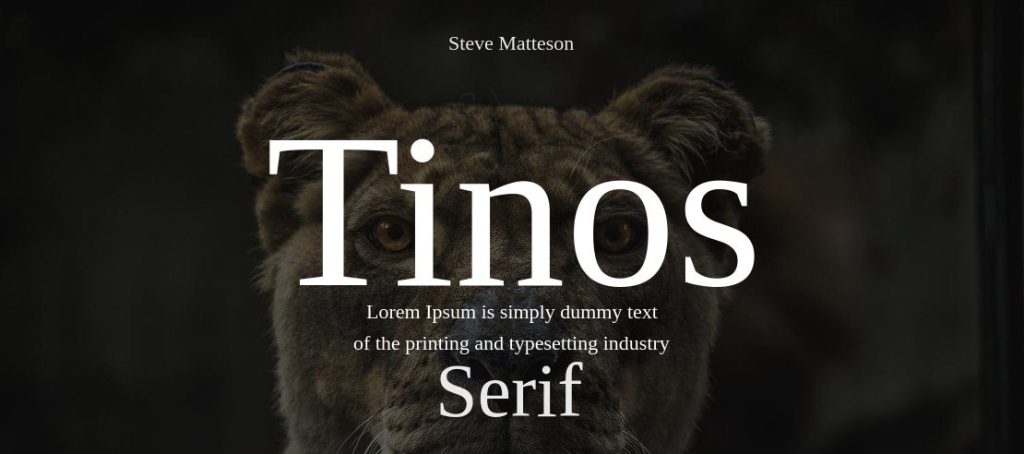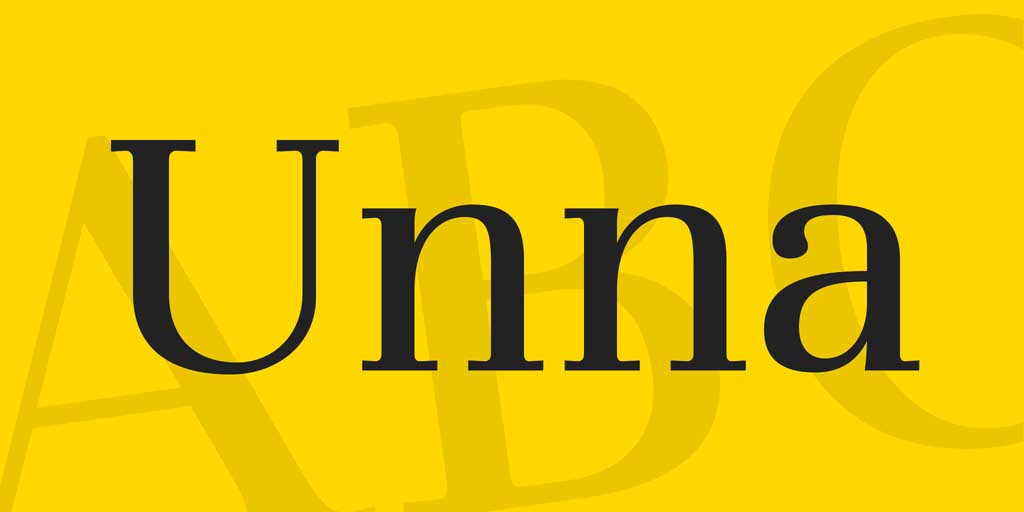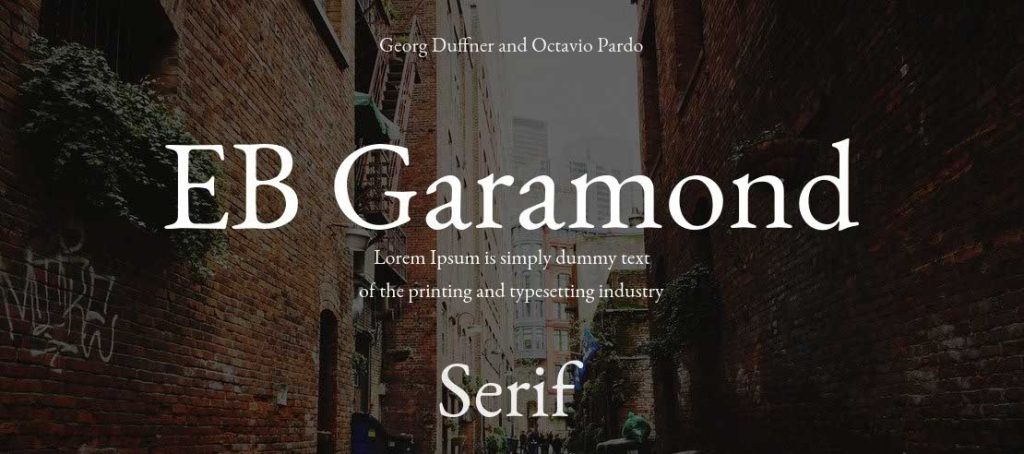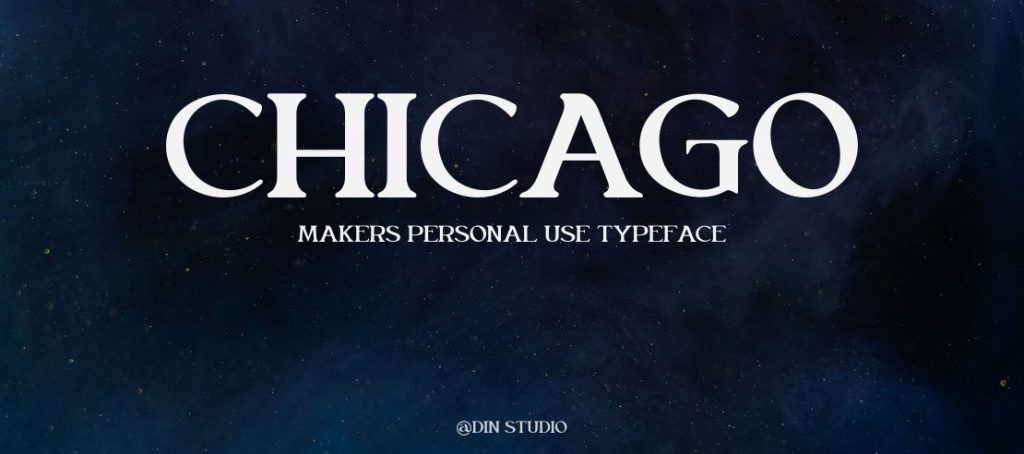
19+ Font Chữ Có Chân Đẹp, Cổ Điển, Việt Hóa Cho Designer
Vẻ đẹp cổ điển và thanh lịch của font chữ có chân giúp thiết kế của bạn trở nên tinh tế hơn. Lựa chọn font chữ đôi khi là một nhiệm vụ khó khăn và đòi hỏi nhiều thời gian của nhà thiết kế. Terus sẽ giới thiệu cho bạn các font có chân đẹp mắt trong bài viết sau để bạn tham khảo cho dự án thiết kế của mình.
I. Font chữ có chân là gì?
Serif font, còn được gọi là font chữ có chân, là loại font chữ có các nét móc hoặc chân nhỏ ở đầu hoặc cuối mỗi ký tự.
Nhiều thiết kế sử dụng font chữ có chân thường, đặc biệt là trong các văn bản hành chính, báo chí hoặc sách xuất bản. Một số thương hiệu sang trọng như Dior, Gucci và Tiffany & Co,… sử dụng font serif trong thiết kế logo của họ vì họ tin rằng những font chữ có chân mang lại cảm giác chuyên nghiệp và sang trọng.
II. Tổng hợp 19+ font chữ có chân đẹp mắt
Terus sẽ giới thiệu những font chữ có chân đẹp mắt từ những font serif cổ điển cho đến những biến thể hiện đại hơn, giúp bạn tìm được những font chữ phù hợp nhất cho thiết kế của mình.
1. Playfair Display
Playfair Display có khả năng tạo ấn tượng thanh lịch và độc đáo cho người nhìn. Playfair Display, được phát triển bởi Claus Eggers Sørensen, lấy cảm hứng từ các kiểu chữ serif cổ điển của thế kỷ 18, nhưng được sửa đổi để phù hợp với thị hiếu hiện đại.
Playfair Display cung cấp sự cân bằng tuyệt vời giữa nét thanh và nét đậm, đảm bảo rằng nội dung dễ đọc và thoải mái cho mắt. Playfair Display có thể được sử dụng làm tiêu đề, bảng quảng cáo và các thành phần quan trọng của thiết kế. Playfair Display là lựa chọn tuyệt vời cho các thương hiệu và những người muốn tạo ra ấn tượng với vẻ đẹp sang trọng, thanh lịch và dễ đọc.
2. Garamond
Claude Garamond đã tạo ra Garamond, một font chữ serif thanh lịch và cổ điển vào thế kỷ 16. Font chữ này, được tạo ra bởi Claude Garamond vào thế kỷ 16, mang đậm dấu ấn của thời kỳ Phục Hưng và được biết đến với sự tinh tế và thanh lịch.
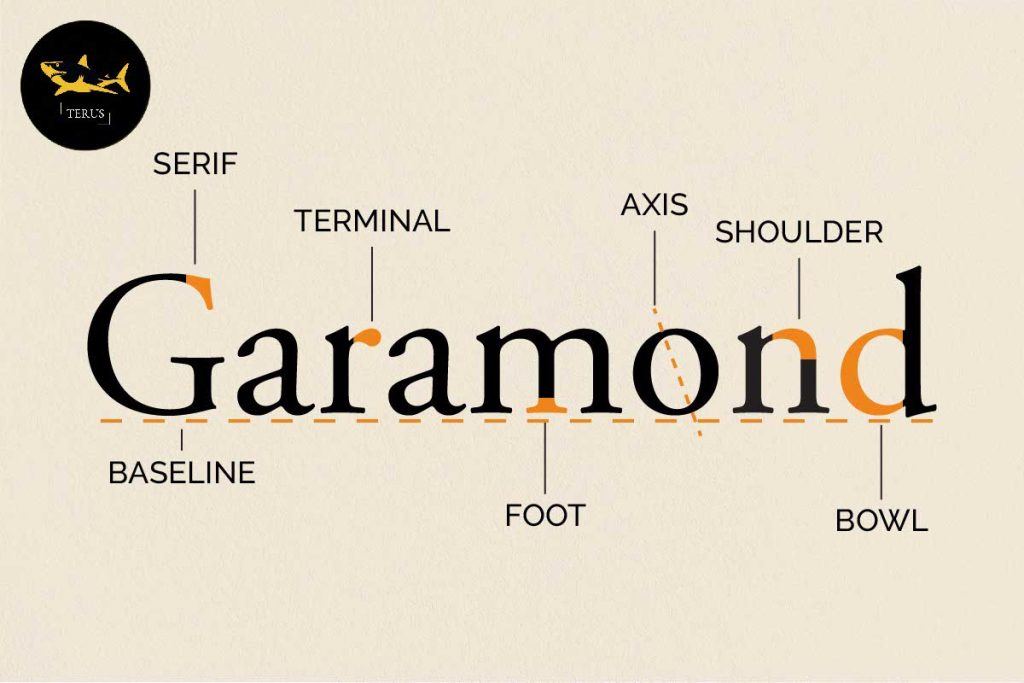
Các đặc điểm chung của Garamond bao gồm các đường nét mềm mại, đối xứng và chân nhỏ, mang lại cho nó vẻ ngoài cổ điển và thanh nhã. Thông thường, font chữ có chân này được sử dụng cho văn bản trong sách, tạp chí và báo, đặc biệt là văn học hoặc các tác phẩm chuyên ngành như văn học, triết học và lịch sử.
3. Didot LT Std Italic
Font Didot LT Std Italic là một biến thể của font chữ Didot, được coi là một trong những font chữ được sử dụng phổ biến nhất hiện nay. Các đường nét cong mềm mại và sự nghiêng nhẹ về phía trước là những đặc điểm nổi bật của Didot LT Std Italic, mang lại cảm giác thanh lịch và uyển chuyển. Các ký tự cân đối và tương phản hoàn hảo, tạo nên một kiểu chữ dễ đọc và phù hợp với nhiều loại dự án thiết kế.
4. Cardo
Font chữ Cardo là một font chữ có chân việt hóa miễn phí dựa trên tiếng Latin và Hy Lạp cổ điển. Cardo, được tạo ra bởi David Perry, mang lại cho bất kỳ văn bản nào cảm giác cổ điển và độc đáo, đặc biệt là các tác phẩm nghệ thuật, sách, văn học cổ điển và tài liệu học thuật.
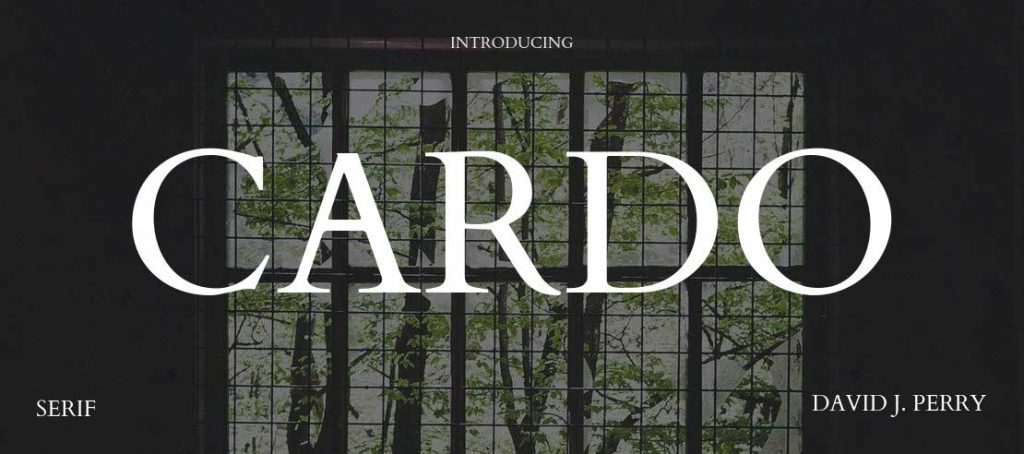
Cardo hỗ trợ nhiều ngôn ngữ, bao gồm tiếng Việt, và có nhiều ký tự độc đáo. Font chữ này có sự cân bằng tuyệt vời giữa nét thanh và nét đậm, giúp người xem đọc văn bản dễ dàng hơn và mang lại cảm giác dễ chịu cho mắt. Một số người cũng sử dụng Cardo cho các loại sách, tạp chí, brochure và catalogue cao cấp.
5. Lora
Cyrus Highsmith đã tạo ra Lora, một font chữ serif hiện đại. Lora là một font chữ serif linh hoạt và hiện đại, phù hợp cho cả in ấn truyền thống và ấn phẩm kỹ thuật số. Lora có khả năng tạo ra cảm giác sang trọng và thanh lịch cho các thiết kế nhờ các nét chữ thanh mảnh và sắc nét. Lora là một lựa chọn tuyệt vời để thiết kế logo hoặc dùng làm tiêu đề vì nó có độ tương phản vừa phải và ký tự dễ đọc.
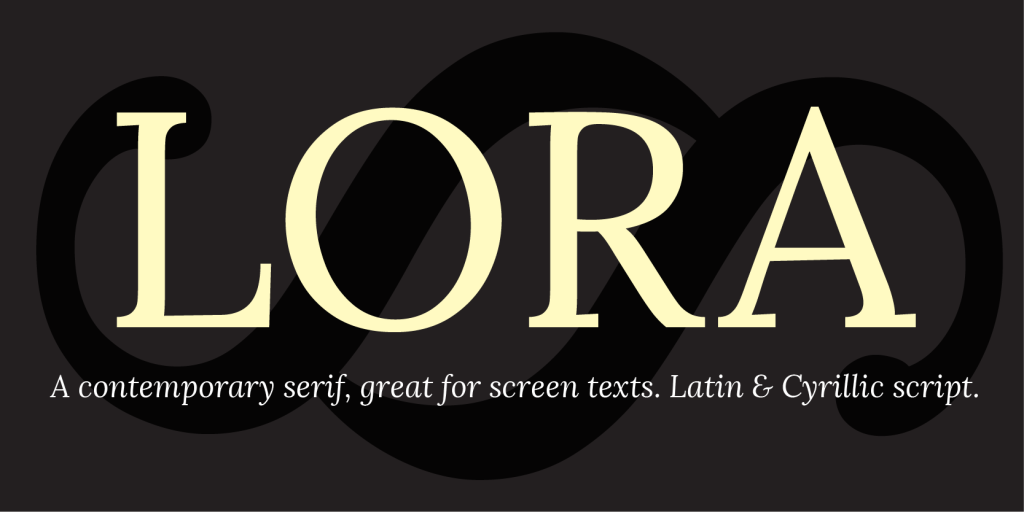
6. Prata
Prata cũng là một font chữ có chân việt hóa hiện đại do Cyrus Highsmith thiết kế. Prata là một biến thể của họ chữ Didone, một loại font serif ra đời vào đầu thế kỷ 19. Ký tự với các móc hình tam giác tạo cảm giác vững chãi và nhẹ nhàng.
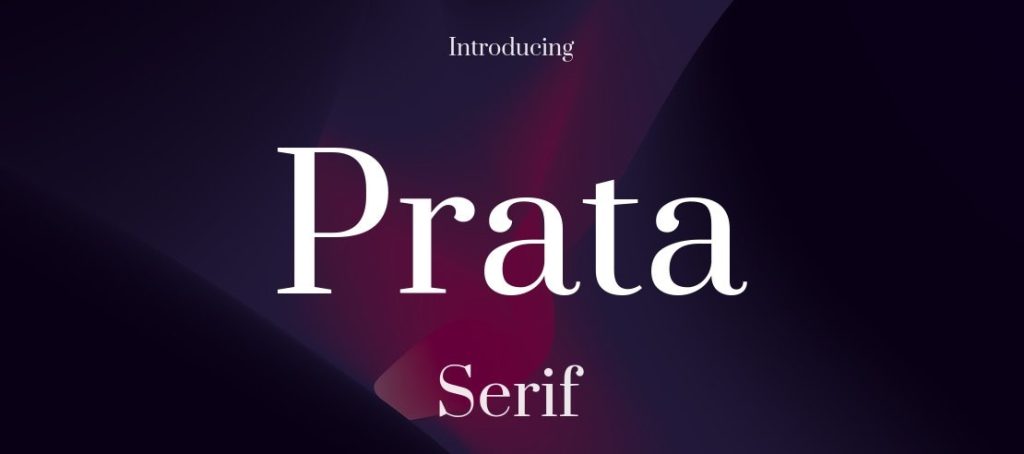
7. Cormorant
Cormorant là một font chữ có chân đa năng và sang trọng có nhiều biến thể, phù hợp với nhiều loại thiết kế như biển hiệu, ấn phẩm và logo thương hiệu. Kiểu dáng thanh lịch và độc đáo của nó mang đến sự tinh tế cho mọi dự án. Ngoài ra, việc kết hợp font chữ này với các font chữ khác và các yếu tố thiết kế khác là đơn giản.
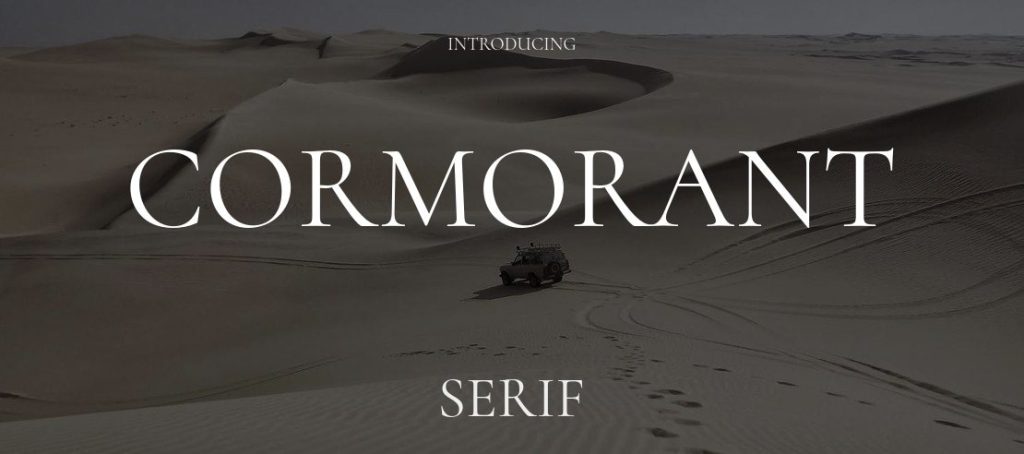
8. Vidaloka
Năm 2011, các nhà thiết kế đồ họa Alexei Vanyashin và Olga Karpushina đã thiết kế Vidaloka. Nhờ đặc điểm dễ đọc ở kích thước lớn, đây là một font tuyệt vời cho các tiêu đề và đoạn văn bản nổi bật. Vidaloka, có độ tương phản cao giữa nét thanh và nét đậm và độ dày vừa phải, giúp nội dung trở nên nổi bật hơn khi sử dụng ở kích thước lớn.
9. The Seasons
My Creative Land xuất bản font chữ có chân sang trọng The Seasons do Elena Genova thiết kế. Font chữ này có thể dễ dàng phân biệt các ký tự vì nó có sự khác biệt rõ ràng giữa nét thanh và nét đậm. Hiện tại, font chữ này đã được bản Việt hóa và có sáu phong cách font khác nhau: tiêu chuẩn, Italic, Bold, Bold Italic, Light và Light Italic.
Sử dụng font chữ có chân sáng tạo: Có rất nhiều font chữ có chân sáng tạo được thiết kế bởi các nhà thiết kế typograpy độc lập.
5. Nên sử dụng font chữ có chân hay font chữ không chân?
Theo Terus, việc lựa chọn font chữ có chân hay font chữ không chân phụ thuộc vào nhu cầu và mục đích sử dụng của bạn:
Font chữ có chân: Nên sử dụng khi bạn muốn tạo ra một ấn tượng thanh lịch, trang trọng và dễ đọc.
Font chữ không chân: Nên sử dụng khi bạn muốn tạo ra một ấn tượng hiện đại, trẻ trung hoặc năng động.